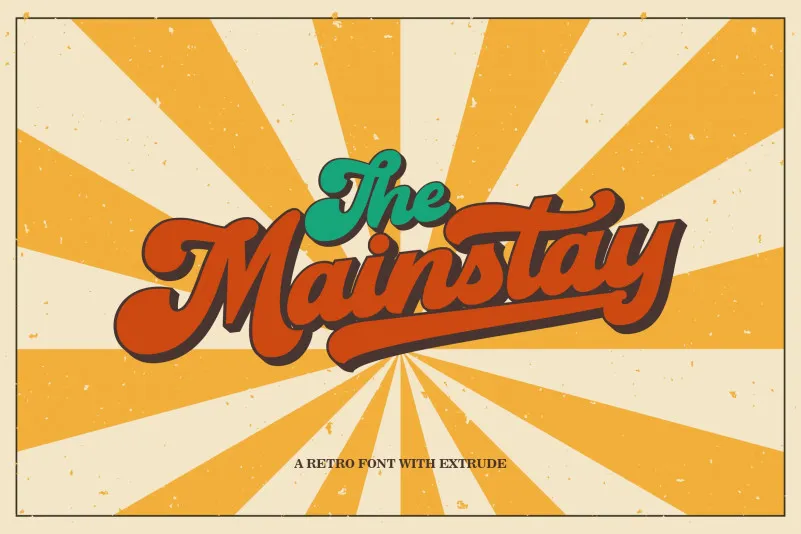
Mainstay Font
A fonte ‘Mainstay Font’ é uma escolha perfeita para quem busca um estilo elegante e contemporâneo no seu design. Desenvolvida por ahweproject, esta font script é uma criação clássica que se apresenta com forte característica e dinamismo, combinando o clássico com a modernidade. Ela é perfeitamente adaptada para títulos e logotipos, dando um toque nostálgico ao seu design. Ideal tanto para editoriais quanto para embalagens ou designs web, Mainstay adicionará uma graça única e funcional à sua obra, tornando-a ainda mais especial e atrativa. Sem dúvida, é a font que você precisa para qualquer projeto gráfico que esteja buscando um toque único de sofisticação e modernidade.